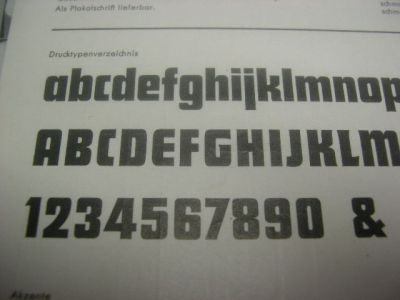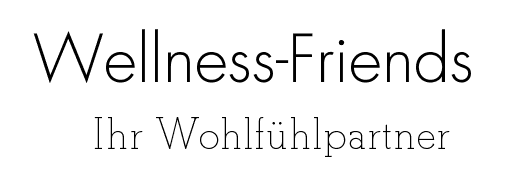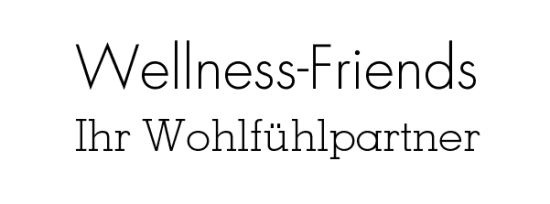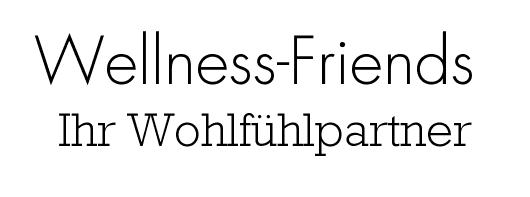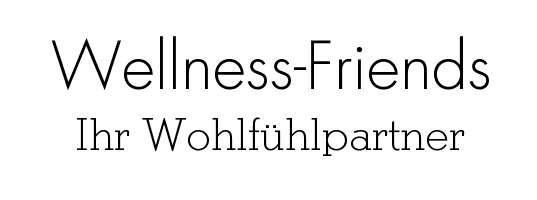
Passende Schrift zu Futura-Logo, Thema Wellness gesucht
Für ein Geschäft, das hochwertige Bäder verkauft, wurde ein Logo mit der Futura light entworfen. Nun suche ich eine dazu passende Schrift, die modern und hochwertig, aber auch lebendig wirkt. Sie soll auf Plakaten zum Einsatz kommen, aber auch für Fließtexte in Flyern oder Briefen verwendet werden können.
Hat jemand von Euch eine Idee?
Die Futura-Familie ist sehr umfangreich.
Andererseits kannst Du die Futura selten mit anderen Serifenlosen mischen.
Also würde ich entweder für die Plakatschrift auf eine Schreibschrift ausweichen, mit der man dann auch recht leicht Wellness assoziieren kann. Und diese Schreibschrift dann auch für die Zwischen-Überschriften in Flyern oder Briefen verwenden.
Oder - warum bleibst Du nicht in der Futura-Familie und kombinierst entweder z.B. eine Dreiviertelfette Futura mit der Mageren? Oder wie gefällt Dir denn die Futura Schlagzeile?
Die Idee, Schreibschriften zum Auflockern auf Plakaten etc. zu verwenden, finde ich gut. Doch ich würde dem Kunden gerne eine Schrift für den Alltagsgebrauch nennen, und die Futura gefällt mir dafür nicht so gut. Ich finde, sie wirkt zu kühl dafür. Gibt es da nicht doch noch eine andere Möglichkeit?
Hmm, welche andere Grotesk passt, ergänzt sich mit der Futura?
Gute Frage.
Wie sieht dein Logo bzw. deine Wortmarke aus - ich denke das solltest du zeigen.
Vielleicht:
auch konstruiert, aber "gemäßigter":
Avenir (bei Linotype schauen)
Proxima Nova
Gotham
als weitere Anregung falls die obigen Schriften nicht passen sollten oder aber zu unlebendig sind - Apex New
@Bleisetzer
die Futura Schlagzeile ist grandios...
Ich liebe die Futura. Und habe einige Grade von allen Schnitten, sogar von der Steilen Futura. Die Futura Black fehlt mir - sie fällt aber auch völlig aus dem Schema, empfinde ich als regelrecht unpassend. Und diese Futura Schlagzeile habe ich auch nicht. Ich finde, sie könnte ohne weiteres als heutige Schrift durchgehen.
Muss es überhaupt eine weitere Endstrichlose sein, vor allem wenn sie auch für Fließtexte verwendet werden soll?
>Muss es überhaupt eine weitere Endstrichlose sein
Schlag mal eine "serifhaltige" vor, würde mich interessieren.
Ich finde diese Slab-serif könnte passen.
Den Begriff "Endstrichlose" habe ich noch nie gehört.
Du schlägst vor, eine Serifenbetonte Linear-Antiqua mit der Futura mager zu mischen? Das ist.. ungewöhnlich? Nein. Das erstaunt mich? Nein.. Das ist.. nein, das geht doch nicht. NEIN. Das finde ich disgusting.
„Endstrichlos“ hat z. B. Jan Tschichold gebraucht, ist doch ein schöner selbsterklärender Begriff. Da Grotesk und Sans Serif schon genannt wurde, einfach eine weitere Bezeichnung!
Hier mögliche Mischungen der Futura Light mit einer Egyptienne:
Futura Light und Beton Light (Gut der Name der Schrift könnte der Wellnessfirma vielleicht nicht passen, sieht doch aber ganz hübsch aus).
Futura Light und Memphis Light
Futura Light und Stymie Light
Futura Light und Rockwell Light
Futura Light mit PMN Caecilia 45 Light
Nun ja. In einer anderen Diskussion vor einigen Tagen hier, in der es um den zur Zeit vorherrschenden Trend bei der Auswahl von Schriften geht, wurde mir erklärt, daß alles erlaubt sei, was gefällt.
In diesem Sinne:
Wenn's Euch gefällt, dann scheint es ja für Euch in Ordnung zu sein.
Mir kommen da Fragen wie:
Wozu fragt Ihr Euch dann überhaupt noch, welche Schriften zueinander passen?
Wozu gibt es dann überhaupt noch Typographen?
Wofür braucht man Euch?
Eure These kann man doch auch konsequent umsetzen, indem man dem Kunden ein Schriftmusterbuch vorlegt und ihn entscheiden läßt. Hauptsache, ihm gefällts.
Für mich ist das nichts, tut mir leid.
Ich kann da nichts mit anfangen.
304_futuralightbetonlight_1.jpg
Jo mei! Kann man mit diesen Schriften tatsächlich Wellness assoziieren? Was ich – als subjektives Subjekt – sehe ist Strenge, Kühle, Konstruktion, Ecken, Kanten, Härte … ich bin kein Anhänger von Feng Shui (weiss ja noch nicht mal, ob das korrekt geschrieben ist, so), aber bei dem Anblick bekomm ich schon etwas Angst, dass ich mir den Kopf anhau.
Nichts gegen die Typen. Aber Wellness?
sie sich häufig zu sehr ähneln. Daher wäre hier mit einer italic-Variante
ein ausreichender Kontrast gewährleistet. Außerdem wird hier auch die
persönliche Note unterstrichen.
Ich betone allerdings noch einmal, dass die vorgeschlagenen Varianten
natürlich nicht die optmalen Lösungen sind, da auch ich behaupte, dass
es eine passendere Schrift als die Futura für diese Branche gibt und ich
auch nicht unbedingt eine konstruierte Grotesk mit einer humanistischen
Serifenlosen mischen würde.
Nichts desto trotz: